かわいい日本語の手書きフォント30選【商用可】
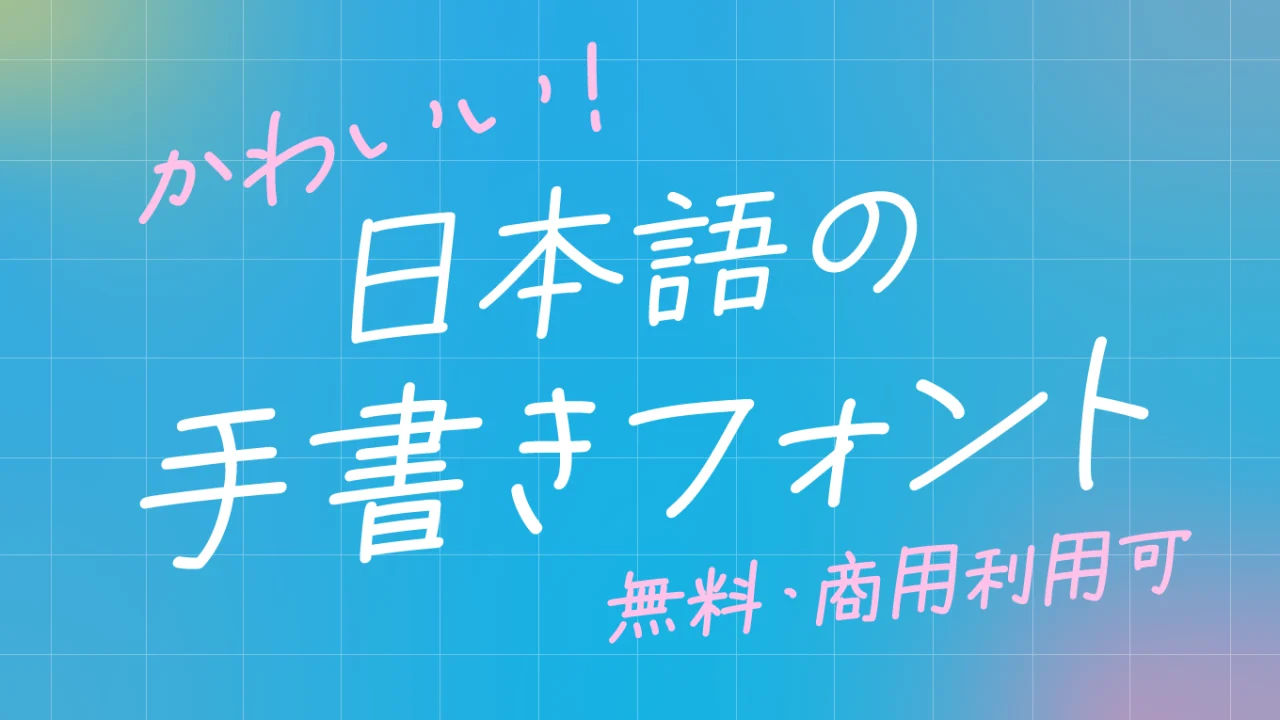
本記事では、おしゃれでかわいい日本語の手書きフォントをご紹介します。
手書きの日本語フリーフォントは数多く公開されており、作り手によって文字の個性や雰囲気が大きく異なります。やさしく可愛らしい女性的な手書き文字から、ラフでかっこいい手書き文字、どこか切なさを感じるエモい手書き文字、マーカーやサインペンで書いたようなナチュラルな文字まで、そのバリエーションは実に豊富です。
デザインの雰囲気に合わせて使い分けられるよう、いくつかお気に入りの手書きフォントを持っておくと、デザインの幅がぐっと広がります。
日本語の手書きフリーフォントのまとめ
以下のサンプル画像は、本記事で紹介しているフォントの一部です。やさしく素朴な文字から、ポップで元気な文字、ノートに書いたような自然な筆跡まで、作者ごとの個性が詰まったかわいい手書きフォントをご紹介しています。手書きならではの温かみや親しみやすさを感じられるフォントばかりなので、ぜひお気に入りの一本を見つけてみてください。
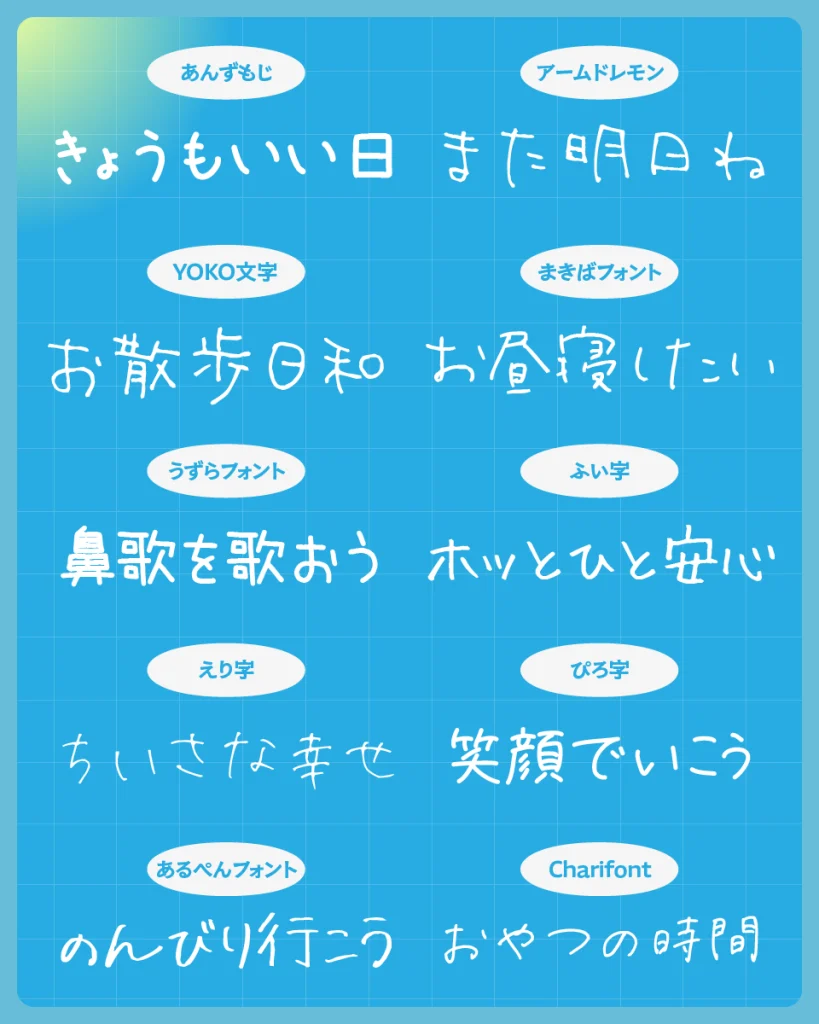
収録文字数が少ないフォントなどは、似ているフォントを複数使い混植で使うことで、未収録文字などを補うなどすることでうまく表示させることができます。
あんずもじ
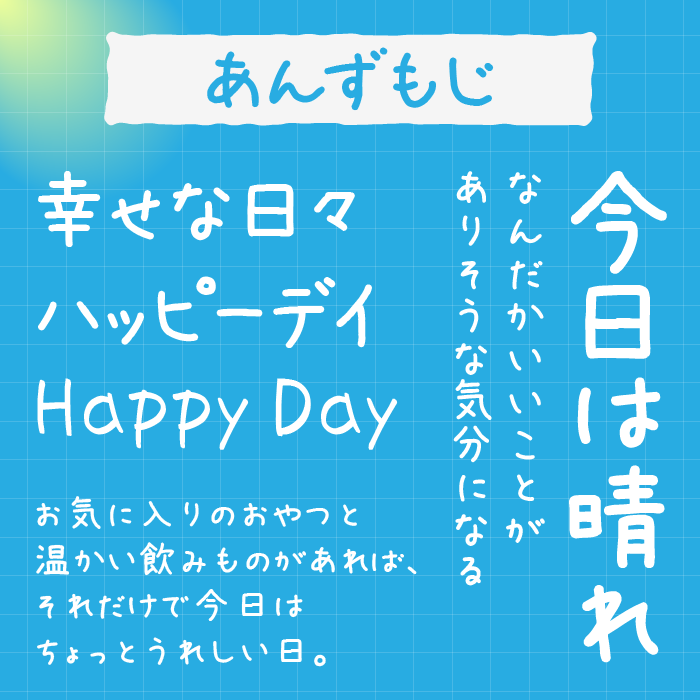
あんずもじは、丸みを帯びた柔らかな線が特徴の手書きフォントです。
自然な筆圧の変化や素直な文字の形から、ノートに丁寧に書いたような温かさが伝わります。読みやすさと可愛らしさのバランスが良く、さまざまなデザインに取り入れやすいフォントです。
アームド・レモン
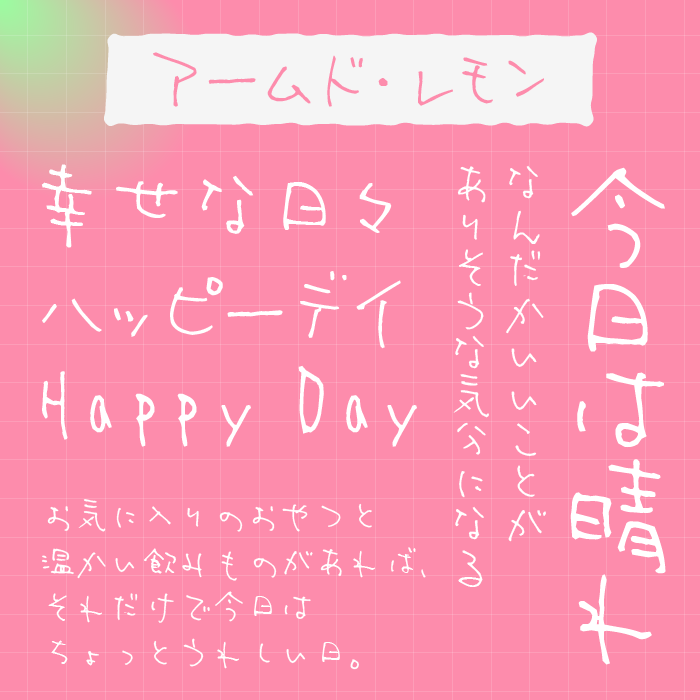
アームドレモンは、細くラフな線で描かれた個性的な手書きフォントです。
力を抜いてさらりと書いたような文字には、気取らない可愛らしさがあります。少し脱力感のある雰囲気が特徴で、一般的な丸文字とは異なる独自の魅力を持っています。
青春感、エモーショナル感、爽快感、なデザインとの相性はピッタリ。収録漢字も第二水準まで収録されています。
無心(むしん)
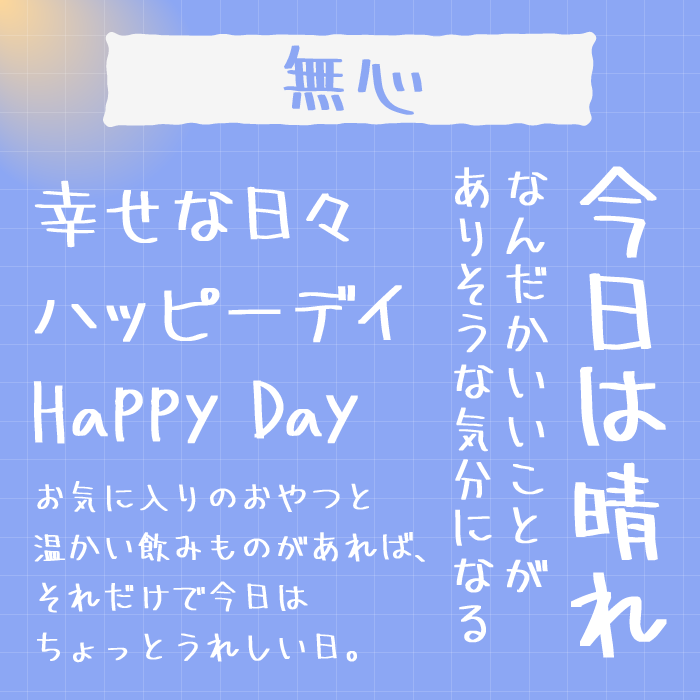
無心フォントは、作者の方が、ひたすら無心で書き殴った手書きフォントです。何のテーマもコンセプトもない、せく作者の方が殴り書きした字をそのままフォントにしたという力強く自由な筆跡が特徴の手書きフォント。
素朴な文字の中に飾らない魅力があり、手書きならではの温かみを自然に伝えることができます。気軽なメッセージや親しみやすいタイトルなど、幅広いシーンで活躍するフォントです。
夜すがら手書きフォント
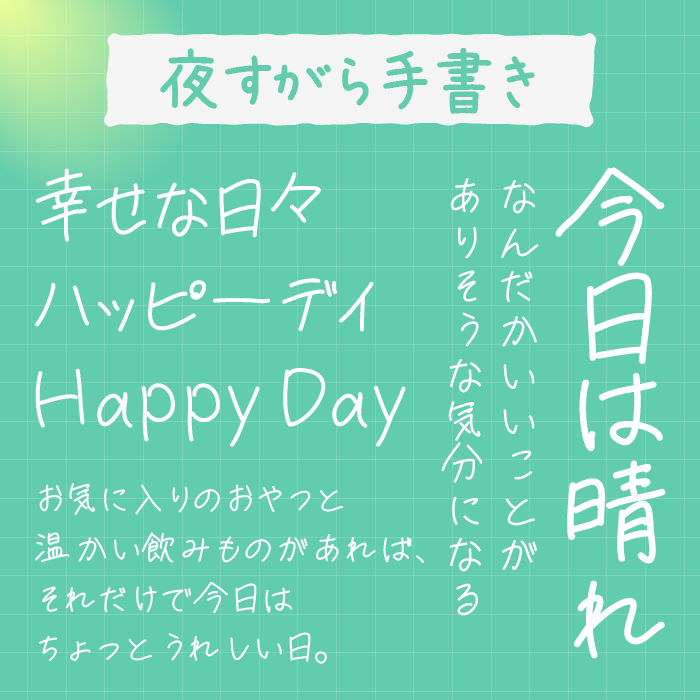
夜すがら手書きフォントは、作者の方が『夜な夜な書いたクセの強い』手書きフォントです。文字が右肩上がりの少しクセの強さが良いアクセントになっており、手書き感を感じることができる素敵なフォントです。
YOKO文字
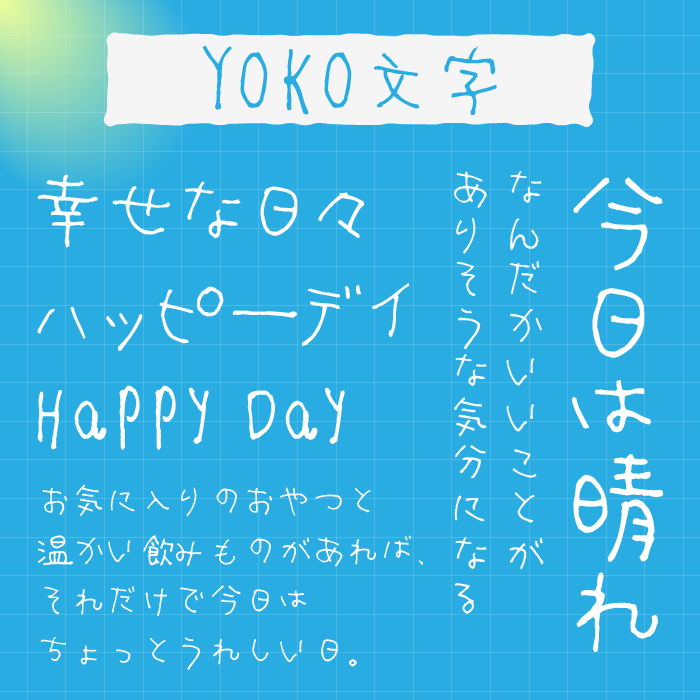
YOKO文字は、鉛筆で走り書きしたような素朴な表情が魅力の手書きフォントです。線の太さや文字の傾きに自然な変化があり、人の手で書いた温もりをしっかり感じられます。どこか懐かしさもあり、日記や手紙を思わせる親近感があります。
メッセージ入りのバナーや手作り感を大切にしたデザイン、個人ブログなどにぴったりです。飾りすぎない自然体の可愛らしさがあるフォントです。
まきばフォント
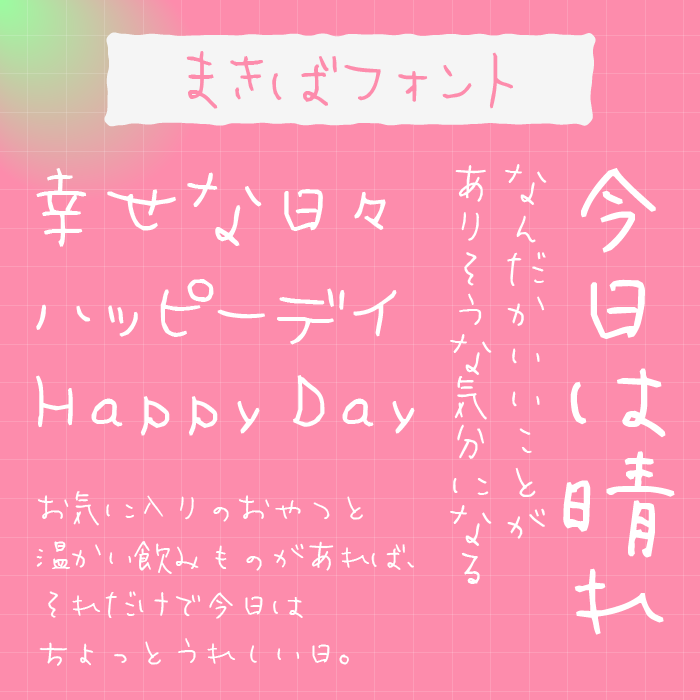
まきばフォントは、自由にのびのびと書いたような文字の表情が印象的な手書きフォントです。
線の揺れや独特な文字の形が、素朴で牧歌的な雰囲気を生み出しています。整いすぎていないからこそ感じられる温かみがあり、見る人に安心感を与えるフォントです。
たぬき油性マジック
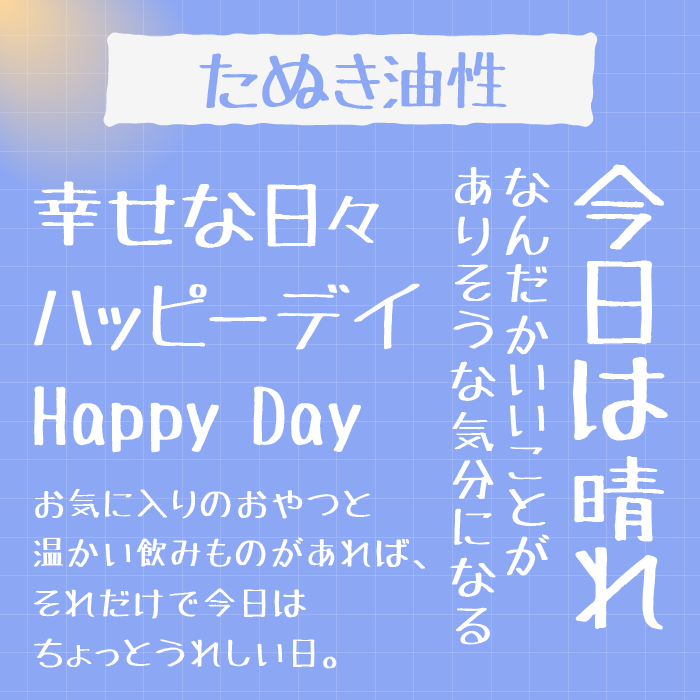
たぬき油性は、マーカーでさらりと書いたような自然な線が魅力の手書きフォントです。
適度な太さと素朴な文字の表情が心地よく、気取らない可愛らしさを演出できます。読みやすさもしっかり確保されているため、見出しから本文まで幅広く使いやすいフォントです。
851マカポップ
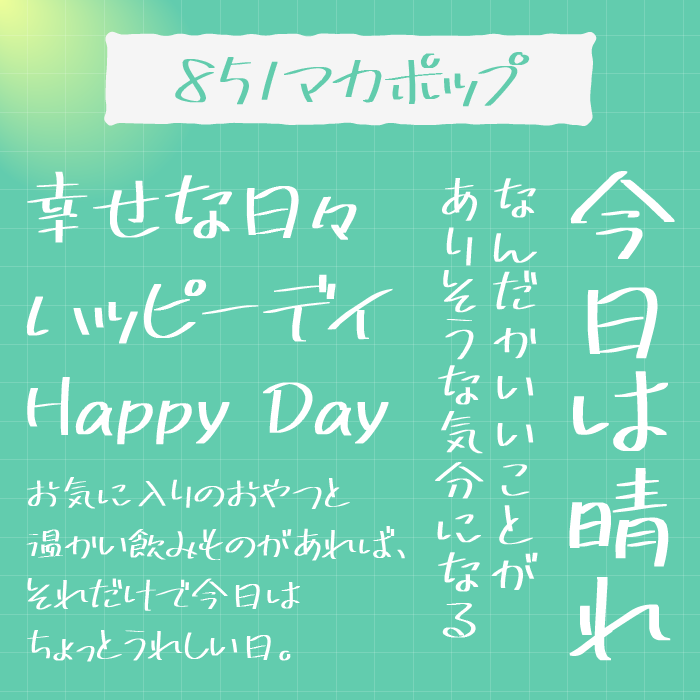
851マカポップフォントは、横太なマーカーでざっくりような手書きフリーフォントです。流れるように書いているマーカー手書き風フォントです。
文字に程よい勢いがあり、楽しさや明るさを表現するのが得意です。イベント告知や子ども向けデザインなど、元気な雰囲気を演出したい場面で活躍するフォントです。
うずらフォント
うずらフォントは、柔らかな丸みと自然な手書き感が魅力のフォントです。
気取らない親近感があり、誰かがそっと書き残したメモのような温もりを感じられます。可愛くて読みやすい手書きフォントを探している方におすすめです。
手紙風のデザインやSNS投稿画像、ハンドメイド作品の紹介などで活躍します。手書きならではの温かな空気感を表現できるフォントです。
アオハルマーカーmini
アオハルマーカーは、青春のノートに書かれた落書きのような爽やかさを感じる手書きフォントです。
細く軽やかな線が特徴で、どこか儚さも漂います。学生向けのデザインやエモーショナルなビジュアルにぴったりなフォントです。
油性マジック(Yusei Magic)
油性マジック(Yusei Magic)フォントは、太めの油性マジックで、1文字づつ正方形に収まるような形になっているユニークな手書きフォント。
スーパーなどのポップ風デザインを制作する際に使ってみると面白いかもしれません。もちろん他にバナーやアイキャッチなどのタイトルなどの目立つ文字に取り入れてみても目を引くデザインが作れそうです。
kawaii手書き文字
kawaii手書き文字は、丸みのある線と素直な文字の形が特徴の王道手書きフォントです。
親しみやすく可愛らしい印象があり、タイトルから本文まで幅広く使えます。手書きならではの温かさを気軽に取り入れられるフォントです。
左利きの彼女
左利きの彼女フォントは、左利きの作者が丁寧に書いた女性らしさがある文字で、とても美しく可憐な手書き文字になっています。
しろくまフォント
ラフさを残しながらも読みやすくまとめられており、自然体の可愛らしさを感じられます。文字の一つひとつに表情があり、温かなコミュニケーションを演出してくれるフォントです。
手書きPOPやブログ見出し、個人制作の作品紹介などにぴったりです。親しみやすさと程よい個性を兼ね備えたフォントです。
charifont
Charifontは、ゆるやかな丸みと素直な線で構成された可愛らしい手書きフォントです。
英字との相性も良く、全体に統一感のあるデザインを作りやすいのが特徴です。柔らかな雰囲気の中にもすっきりとした読みやすさがあり、幅広いシーンで使いやすいフォントです。